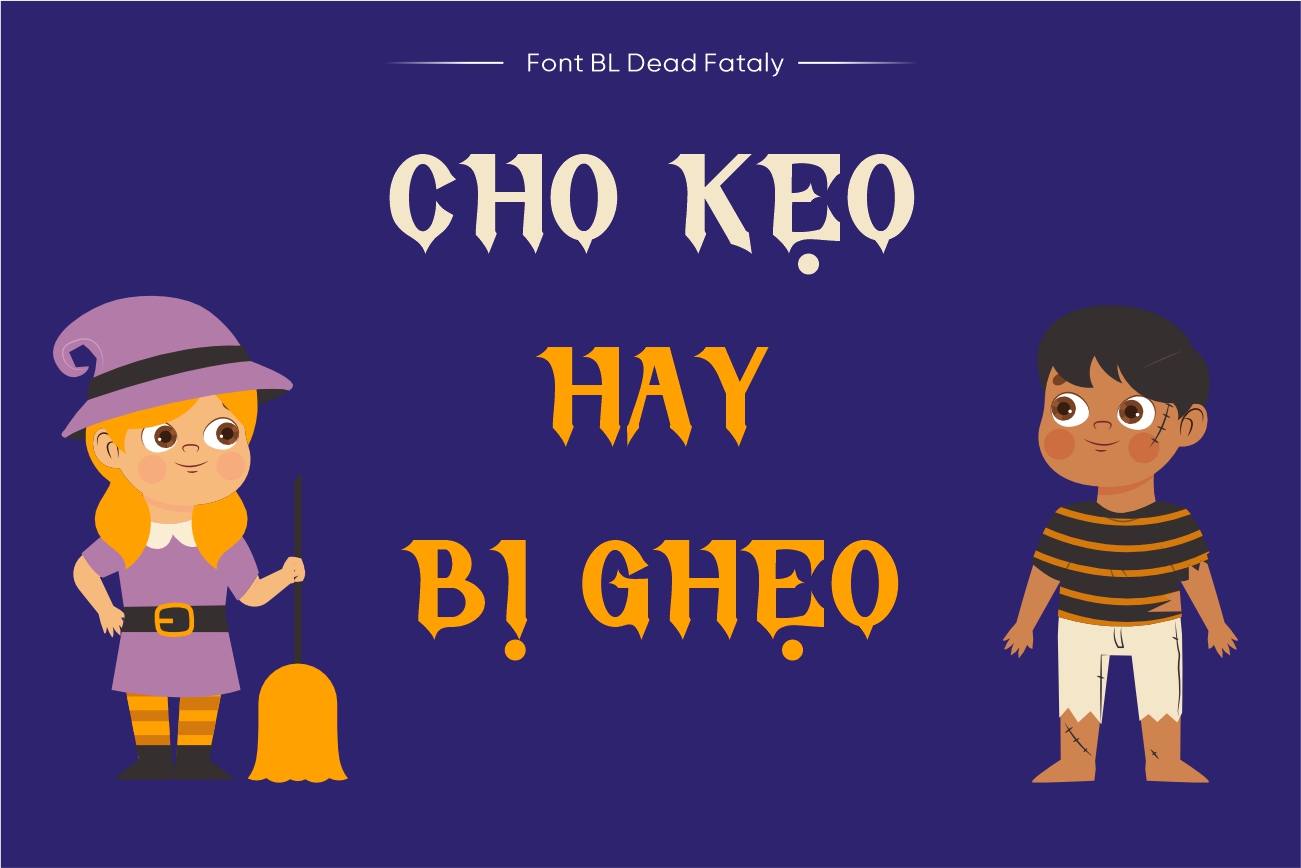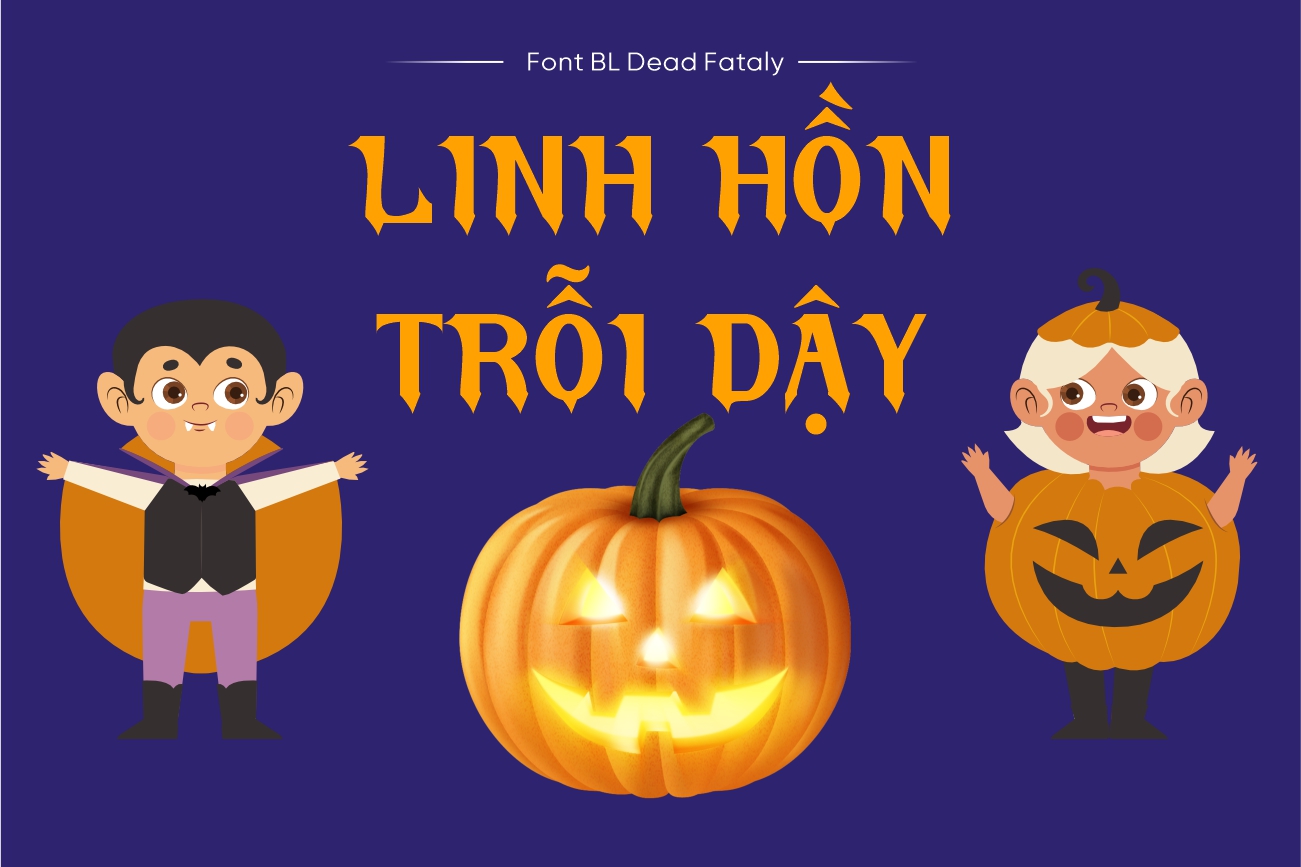
BL Dead Fataly - Font Gothic đầy ma mị
BL Dead Fataly là phiên bản Việt hóa từ bộ font Dead Fataly do Maiko Hatta thiết kế, mang đậm tinh thần phong cách gothic – kinh dị với bầu không khí lạnh lẽo, đen tối và đầy kịch tính thị giác. Ngay từ cái nhìn đầu tiên, bộ font đã tạo cảm giác dữ dội, bí ẩn và rùng rợn, như bước vào một thế giới đầy bóng tối, linh hồn, quỷ dữ và những câu chuyện ma ám ám ảnh.
Team BL đã thực hiện Việt hóa BL Dead Fataly một cách tỉ mỉ, đảm bảo font hiển thị tiếng Việt đầy đủ dấu, sắc nét và cân bằng về hình dáng ký tự, giúp người dùng Việt dễ dàng khai thác trọn vẹn giá trị mạnh mẽ mà font mang lại trong các thiết kế sáng tạo.
Kiểu dáng của BL Dead Fataly tập trung vào những chữ cái sắc nhọn, góc cạnh, đường nét kéo dài đầy đe dọa và cảm giác như được khắc từ bóng tối. Chính đặc trưng này giúp bộ font trở thành lựa chọn cực kỳ nổi bật cho những dự án cần yếu tố rùng rợn, ám ảnh và kích thích cảm xúc. BL Dead Fataly đặc biệt phù hợp cho các thiết kế chủ đề Halloween, phim kinh dị, poster band rock/metal, logo cá tính hoặc bìa truyện tranh ma, nơi cần sự ấn tượng mạnh ngay từ ánh nhìn đầu tiên. Khi xuất hiện trong bố cục thiết kế, bộ font không chỉ đóng vai trò là chữ viết, mà còn như một yếu tố đồ họa góp phần xây dựng bầu không khí chết chóc, lạnh lẽo và đầy kịch tính.
Nguồn gốc cảm hứng của Dead Fataly đến từ thế giới của bóng đêm, những câu chuyện rùng rợn và tinh thần nổi loạn đầy bạo liệt. Khi trở thành BL Dead Fataly, bộ chữ vẫn giữ nguyên cái hồn đó nhưng trở nên gần gũi hơn với môi trường sáng tạo Việt Nam nhờ khả năng hiển thị tiếng Việt linh hoạt. Nếu bạn đang cần một bộ font mang phong cách gothic – kinh dị, truyền tải trọn vẹn cảm giác dữ dội, bí ẩn và rùng rợn, đồng thời thực sự phù hợp cho các thiết kế chủ đề Halloween, phim kinh dị, poster band rock/metal, logo cá tính hoặc bìa truyện tranh ma, thì BL Dead Fataly chắc chắn là lựa chọn mang lại năng lượng mạnh mẽ, đậm chất nghệ thuật và đủ sức gây ám ảnh cho người xem ngay từ cái nhìn đầu tiên.